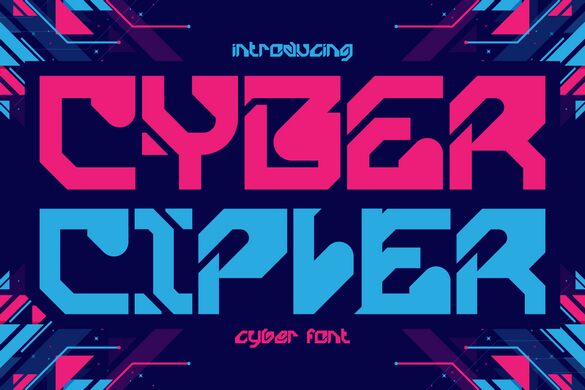
Cyber Cipher von Shanaf Studio ist eine kostenlose, futuristische Display-Schrift, die durch abgeschnittene Ecken, steile Diagonalen und präzise Einschnitte besticht – als bestünden die Buchstaben aus segmentierten Schaltkreisen. Die kompakte Silhouette mit ihren harten Kanten verleiht dem Design einen mechanischen Rhythmus, der weit über bloße geometrische Formen hinausgeht.
Diese Struktur macht die Schrift ideal für kurze, wirkungsvolle Titel: ob für Game-Overlays, E-Sports-Branding, Sci-Fi-Poster, Tech-Event-Grafiken oder Streaming-Thumbnails. Überall dort, wo kantige Akzente gefragt sind – insbesondere in Logos oder Headern –, sorgt Cyber Cipher für eine digitale, systemorientierte Textur anstelle von gewöhnlichen Blockbuchstaben.